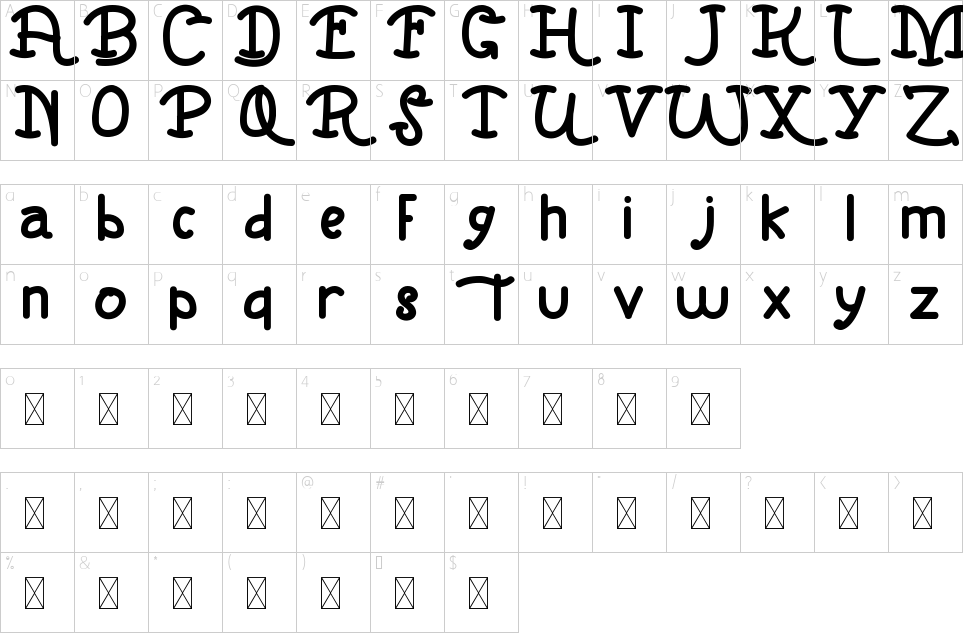
A Playground Kids Font é uma opção divertida e acessível para criar texto colorido e divertido para projetos infantis. Desenvolvida pelo designer desconhecido vintype, a fonte vem em versões compatíveis com Windows e Mac. Ela é perfeita para enriquecer o conteúdo educativo ou criar cartões de aniversário e desenhos animados. Através da fonte Playground Kids, os criadores de conteúdo podem tornar seus projetos ainda mais atraentes e encorajar a criatividade dos pequenos. A fonte já foi baixada 2.476 vezes, mostrando seu valor e popularidade. Se você busca adicionar um toque de diversão a projetos infantis, esta é uma fonte excelente para começar.